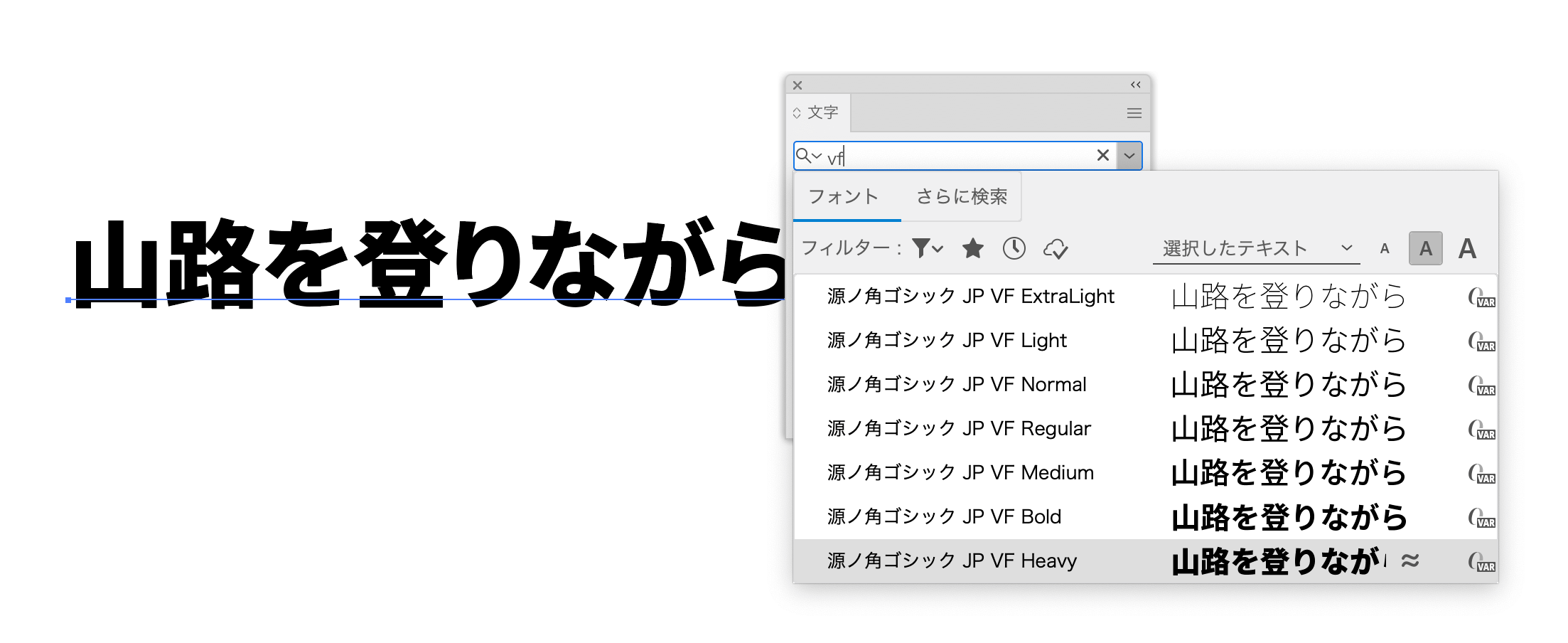
「フォントの日 2021」と源ノ角ゴシックのバリアブルフォント化
4月10日は「フォントの日」。4(フォン)10(ト)の語呂合わせに由来します。
日付は「フォ(4=four)ント(10)」と読む語呂合わせから。デザインの重要な要素となっている「フォント」にあらためて注目してもらうことが目的。記念日は2017年(平成29年)に一般社団法人・日本記念日協会により認定・登録された。
ちなみに、そのタイミングで「源ノ明朝」がリリースされました。
「源ノ角ゴシック」のバリアブルフォント化
もうひとつの話題が「源ノ角ゴシック」のバリアブルフォント化です。ウェイトに依存しない、いわば「無制限ウェイト」として使えるようになります。
タイプフェイスデザイナーの西塚涼子さんがツイートされているように、バリアブルなのは「ウェイト」のみ。
細いウエイトと太いウエイトから中間生成されるとのことですが、なかなかスゴい!!!
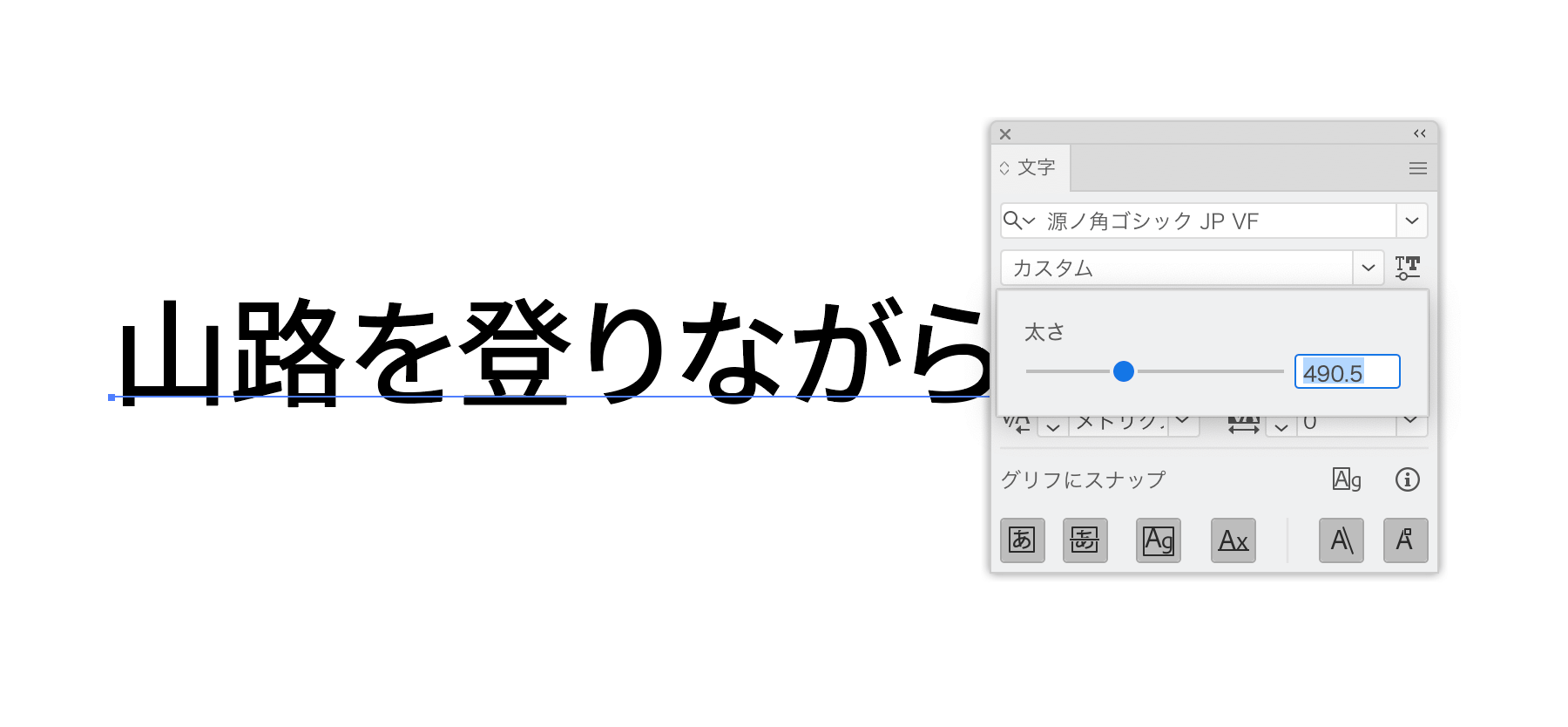
アウトライン化
アウトライン化を視野に入れたワークフローでは「源ノ角ゴシック VF(バリアブル版)」を使うとき、[パスファインダー(追加)]を適用しておくとよさそうです。これによって、アピアランスの分割時にバラバラにならずに結合されます。
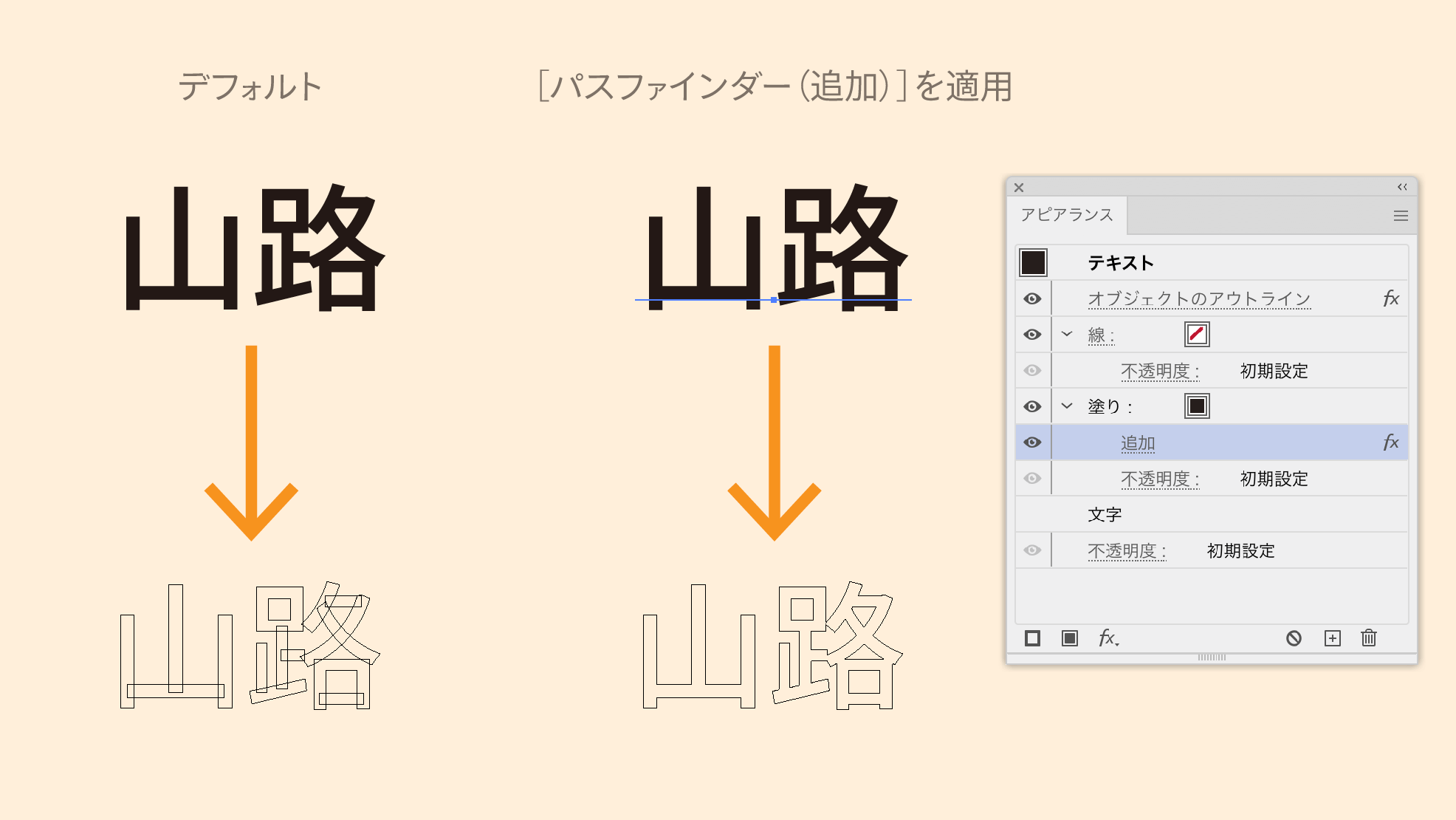
Googleからもリリース
「源ノ角ゴシック」=「Source Han Sans」≒「Noto Sans Japanese」のため、Googleからもリリースされています。
ややこしいですね…
合成フォント
バリアブルフォントの使いどころは、ズバリ「合成フォント」だと思うのですが、IllustratorやInDesignで実装するような気配は感じません…
「源ノ角ゴシック」がバリアブルになった!と沸いています。
「小書きのかな」を小さく扱うと、細く見えてしまうので、太めのウェイトを当てます。
Illustrator/InDesignでは、合成フォントにて行いますが、ここで「バリアブル」にて微調整できると理想。#フォントの日 pic.twitter.com/eFKyEA2W5A
ウェブでも
CSSでもバリアブルフォントが扱える。
font-variation-settingsでパラメータを調整で可能。
その他のバリアブルフォント
すでに入っている欧文のバリアブルフォント
アドビからは次の6フォントがバリアブルフォントとしてリリースされており、IllustratorやInDesignで利用可能になっています。
砧書体制作所
まだ制作中とのことですが、砧(きぬた)書体制作所さんの取り組みがおもしそう!その名も『うゴ』!!!
たづがね角ゴシック
実は日本語フォントのバリアブル化は「たづがね角ゴシック」と「たづがね角ゴシックInfo」が先陣を切って2020年に行われています。
「太さ」のパラメーターを変更すると、ウェイトは「カスタム」と表示されます。